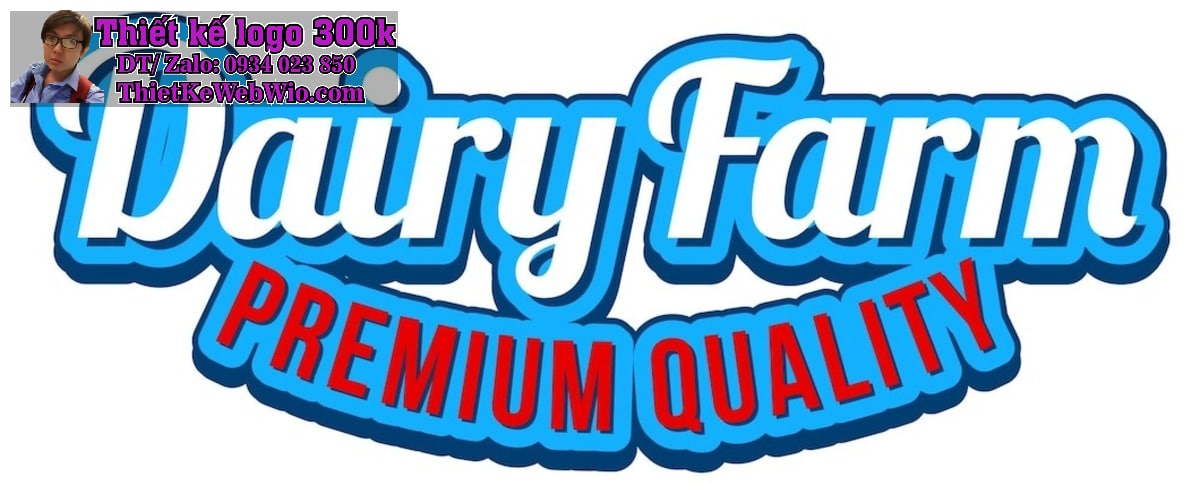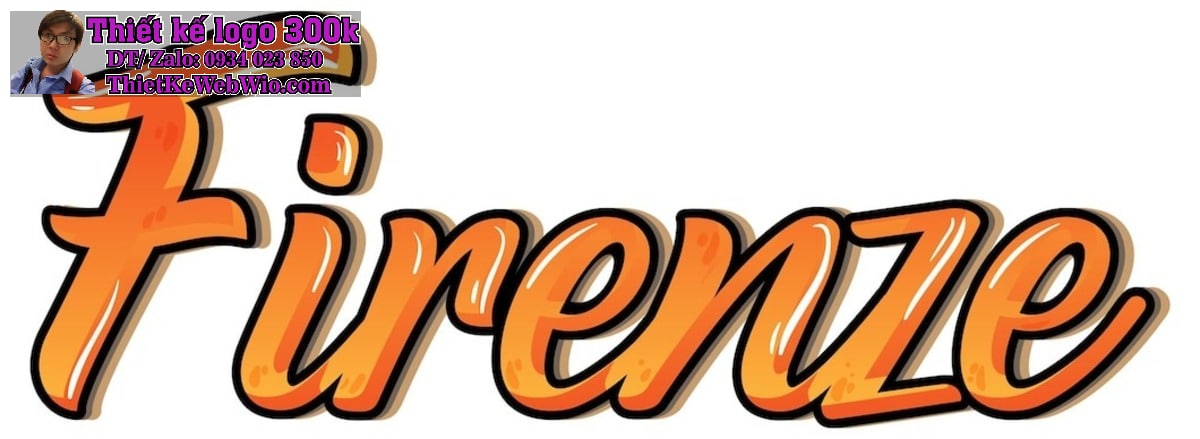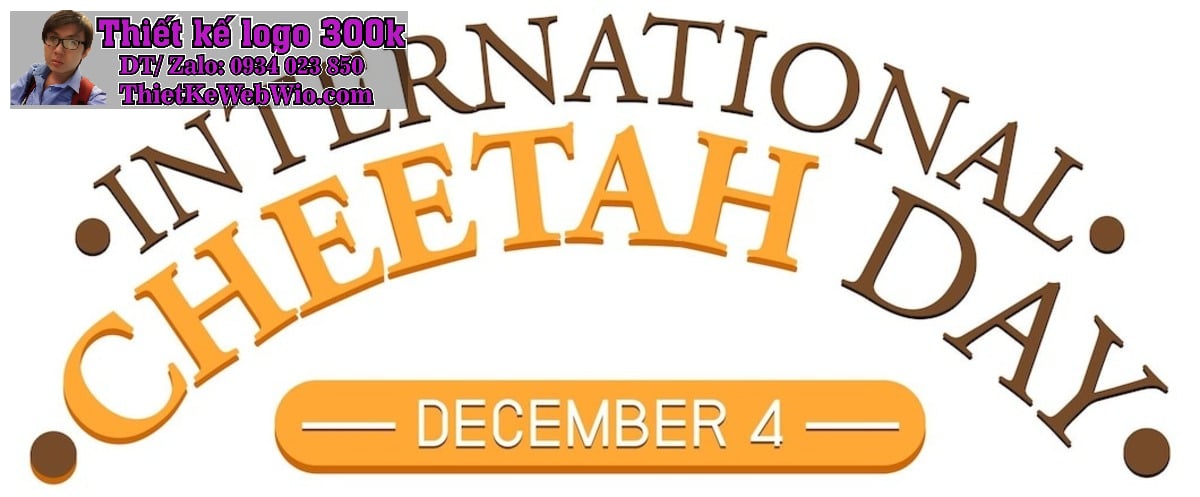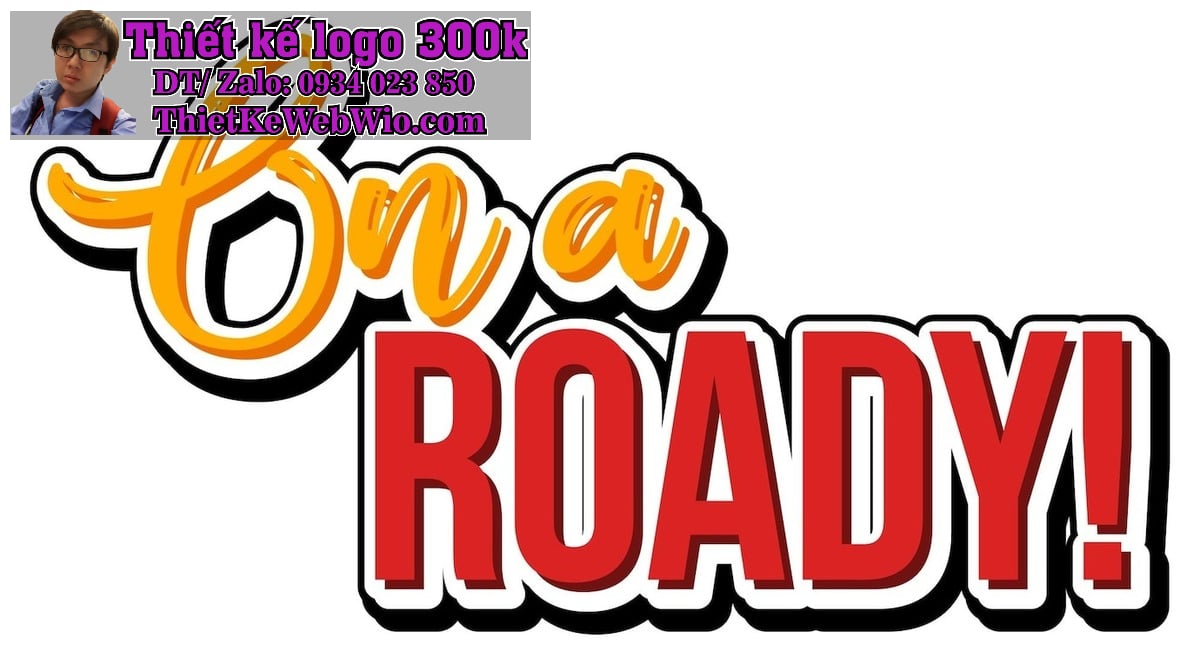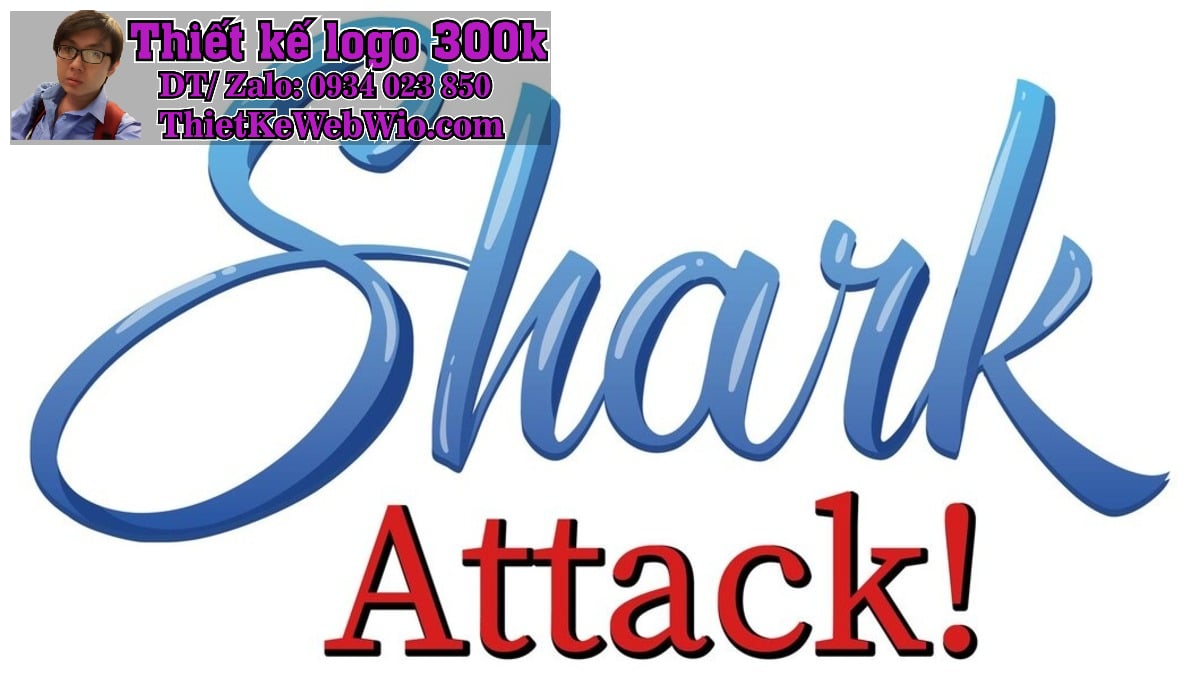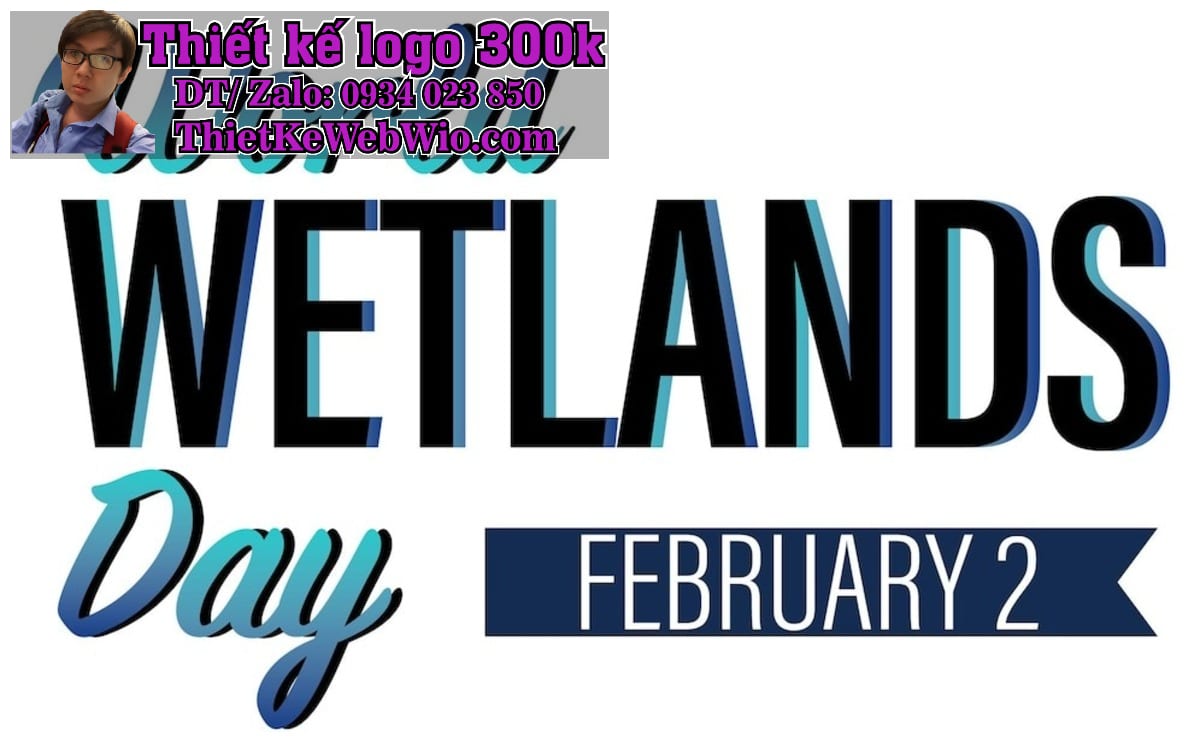
Font chữ là yếu tố quan trọng trong việc thiết kế bảng hiệu, bởi nó không chỉ ảnh hưởng đến tính thẩm mỹ mà còn đến khả năng truyền tải thông tin tới người xem. Trong thế giới thiết kế font chữ trong thiết kế bảng hiệu ngày nay, việc lựa chọn font chữ không chỉ dừng lại ở việc chọn một kiểu chữ đẹp mà còn đòi hỏi sự kết hợp hài hòa giữa mục tiêu quảng cáo, thông điệp và đối tượng người tiêu dùng. Dưới đây, chúng ta sẽ đi sâu vào tìm hiểu tầm quan trọng của font chữ trong thiết kế bảng hiệu và cách lựa chọn font chữ phù hợp cho từng loại bảng hiệu cụ thể.
1. Tầm quan trọng của font chữ trong thiết kế bảng hiệu
Khi nhìn vào một bảng hiệu, điều đầu tiên mà khách hàng chú ý chính là kiểu dáng và cách sắp xếp thông tin. Font chữ đóng vai trò cốt lõi trong việc truyền tải thông điệp mà doanh nghiệp muốn gửi đến người tiêu dùng. Nếu font chữ được chọn không phù hợp,font chữ trong thiết kế bảng hiệu có thể trở nên khó đọc, không chuyên nghiệp hoặc thậm chí không gây được ấn tượng. Font chữ có thể tác động đến nhận thức của người xem về thương hiệu, dịch vụ hoặc sản phẩm mà bạn đang quảng cáo. Một font chữ đẹp, hài hòa sẽ giúp bảng hiệu trở nên bắt mắt, dễ tiếp cận và dễ đọc hơn.
- Thẩm mỹ: Font chữ góp phần tạo nên sự hài hòa trong tổng thể thiết kế. Một font chữ trong thiết kế bảng hiệu có thể trở nên thô kệch hoặc tinh tế tùy vào sự lựa chọn font chữ.
- Nhận diện thương hiệu: Các thương hiệu lớn thường sử dụng font chữ riêng biệt để tạo dấu ấn nhận diện thương hiệu. Font chữ độc đáo sẽ giúp khách hàng dễ dàng nhớ đến thương hiệu của bạn.
- Khả năng đọc: Font chữ quá phức tạp sẽ làm giảm khả năng đọc hiểu của người xem. Điều này cực kỳ quan trọng với các font chữ trong thiết kế bảng hiệu ngoài trời hoặc những nơi mà người xem chỉ có vài giây để tiếp nhận thông tin.
2. Những loại font chữ trong thiết kế bảng hiệu phổ biến trong thiết kế bảng hiệu
Hiện nay, có hàng ngàn kiểu font chữ khác nhau mà nhà thiết kế có thể lựa chọn. Tuy nhiên, không phải tất cả đều phù hợp cho font chữ trong thiết kế bảng hiệu Dưới đây là một số loại font chữ thường được sử dụng trong lĩnh vực này:
Font chữ không chân (Sans-serif)
Font chữ không chân, như Arial, Helvetica, là loại font chữ đơn giản, dễ đọc và thường được sử dụng cho các bảng hiệu lớn hoặc ngoài trời. Vì tính rõ ràng, không cầu kỳ, sans-serif thường là lựa chọn lý tưởng cho các font chữ trong thiết kế bảng hiệu yêu cầu thông tin dễ nắm bắt, đặc biệt trong môi trường ánh sáng yếu hoặc khoảng cách xa.
Font chữ có chân (Serif)
Font chữ có chân, như Times New Roman, Georgia, mang lại cảm giác truyền thống, cổ điển và sang trọng. Chúng thường được sử dụng trong các bảng hiệu cần sự trang trọng hoặc nhắm vào các đối tượng khách hàng cao cấp. Tuy nhiên, trong một số trường hợp, font chữ có chân có thể khó đọc khi sử dụng trên các bảng hiệu ngoài trời hoặc ở cỡ chữ quá nhỏ.
Font chữ viết tay (Script)
Font chữ viết tay mang lại cảm giác mềm mại, nghệ thuật và thân thiện. Đây là lựa chọn tốt cho các font chữ trong thiết kế bảng hiệu mang tính nghệ thuật, cá nhân hóa, như các bảng hiệu trong ngành thời trang, quán cà phê, nhà hàng nhỏ. Tuy nhiên, việc lạm dụng font chữ viết tay có thể làm cho bảng hiệu trở nên khó đọc và rối mắt.
Font chữ hiện đại (Modern)
Font chữ hiện đại có đường nét mạnh mẽ, góc cạnh và thường mang lại cảm giác sáng tạo, đổi mới. Đây là lựa chọn tốt cho các thương hiệu muốn thể hiện sự khác biệt, độc đáo và hướng đến khách hàng trẻ tuổi.
3. Cách chọn font chữ trong thiết kế bảng hiệu phù hợp cho từng loại bảng hiệu
Việc lựa chọn font chữ cho bảng hiệu cần được dựa trên một số tiêu chí quan trọng như đối tượng khách hàng, mục tiêu quảng cáo và vị trí của bảng hiệu. Dưới đây là những hướng dẫn cụ thể giúp bạn chọn font chữ trong thiết kế bảng hiệu phù hợp cho từng loại bảng hiệu.
Bảng hiệu ngoài trời
font chữ trong thiết kế bảng hiệu ngoài trời thường phải cạnh tranh với rất nhiều yếu tố khác như thời tiết, ánh sáng và các bảng hiệu xung quanh. Vì thế, font chữ sử dụng cho bảng hiệu ngoài trời cần rõ ràng, đơn giản và dễ đọc từ khoảng cách xa. Các font chữ sans-serif thường là lựa chọn tối ưu cho các bảng hiệu ngoài trời, vì chúng đảm bảo tính rõ ràng và dễ nhận diện.
Bảng hiệu trong nhà
Với các font chữ trong thiết kế bảng hiệu trong nhà, bạn có thể linh hoạt hơn trong việc chọn font chữ. Tuy nhiên, cần lưu ý rằng không phải mọi font chữ đều phù hợp với môi trường ánh sáng trong nhà. Font chữ serif có thể mang lại sự sang trọng, nhưng nếu được sử dụng trong không gian quá nhỏ, chúng có thể trở nên khó đọc.
Bảng hiệu thương hiệu
font chữ trong thiết kế bảng hiệu thương hiệu cần phải mang tính nhận diện cao và phù hợp với giá trị cốt lõi của thương hiệu. Một số thương hiệu lớn thường sử dụng font chữ thiết kế riêng, tạo sự độc đáo và khác biệt. Điều này giúp khách hàng dễ dàng nhận ra thương hiệu ngay từ cái nhìn đầu tiên.
Bảng hiệu quảng cáo sự kiện
Đối với các sự kiện quảng cáo ngắn hạn, font chữ cần phải thật nổi bật và dễ đọc. Sử dụng các font chữ đơn giản nhưng đậm nét sẽ giúp thu hút sự chú ý của người xem một cách nhanh chóng. Font chữ hiện đại hoặc sans-serif là lựa chọn thường gặp trong trường hợp này.